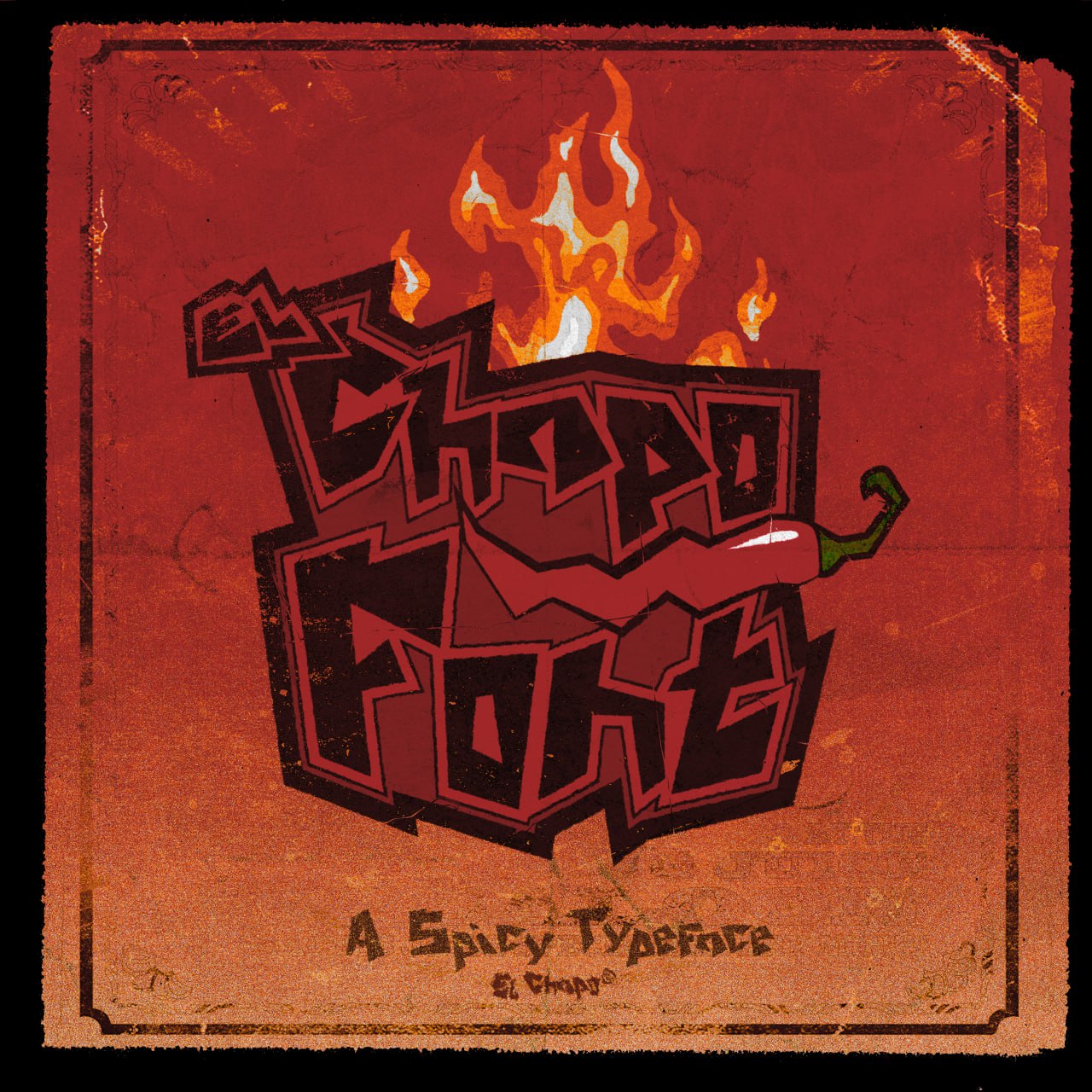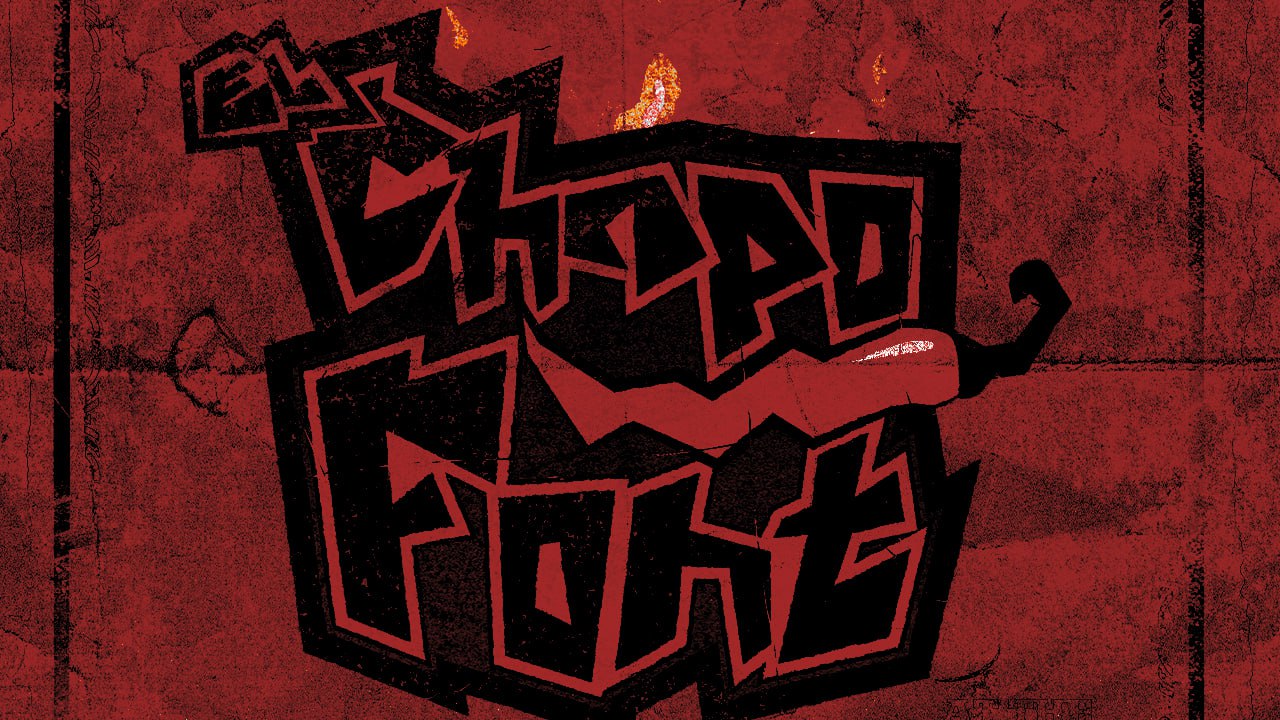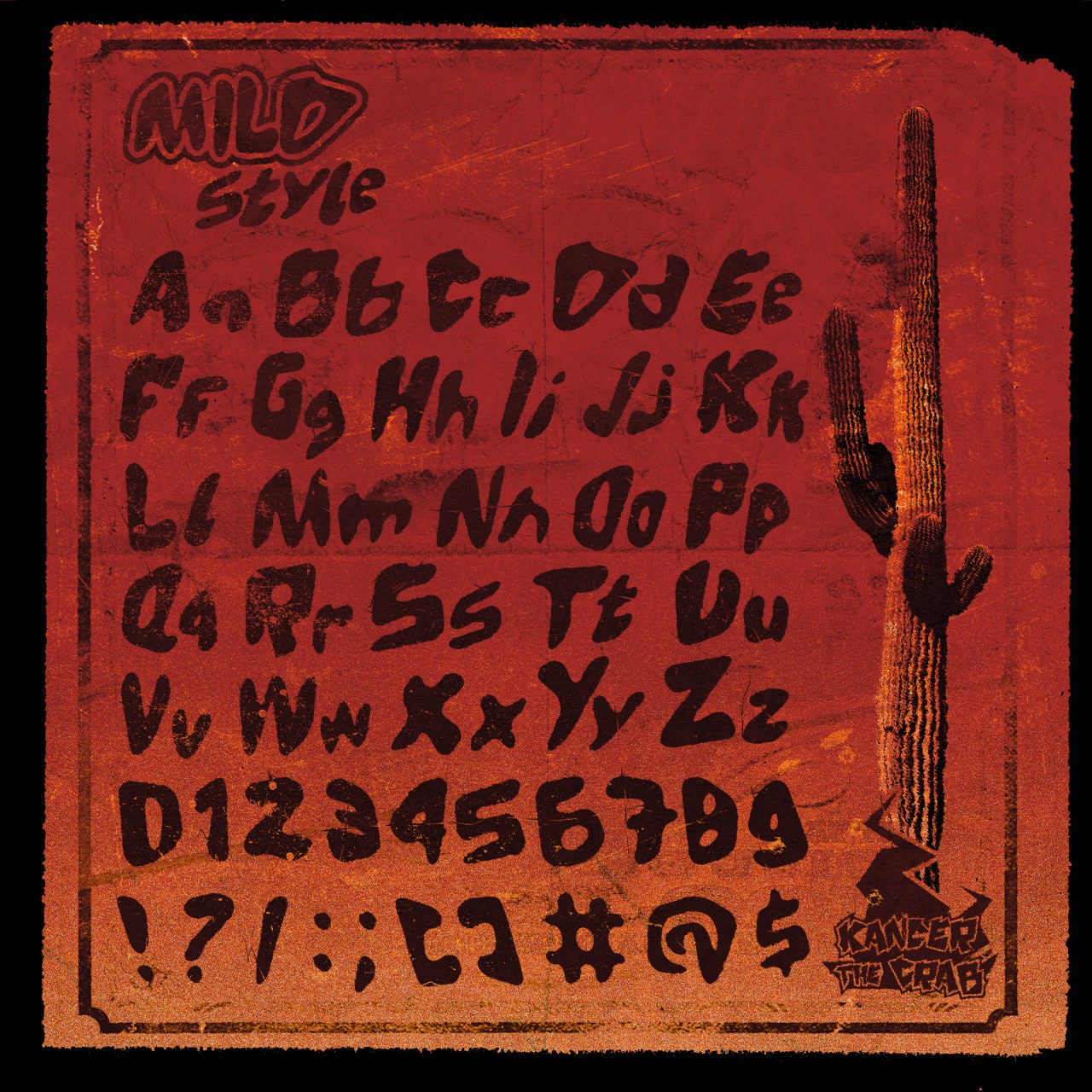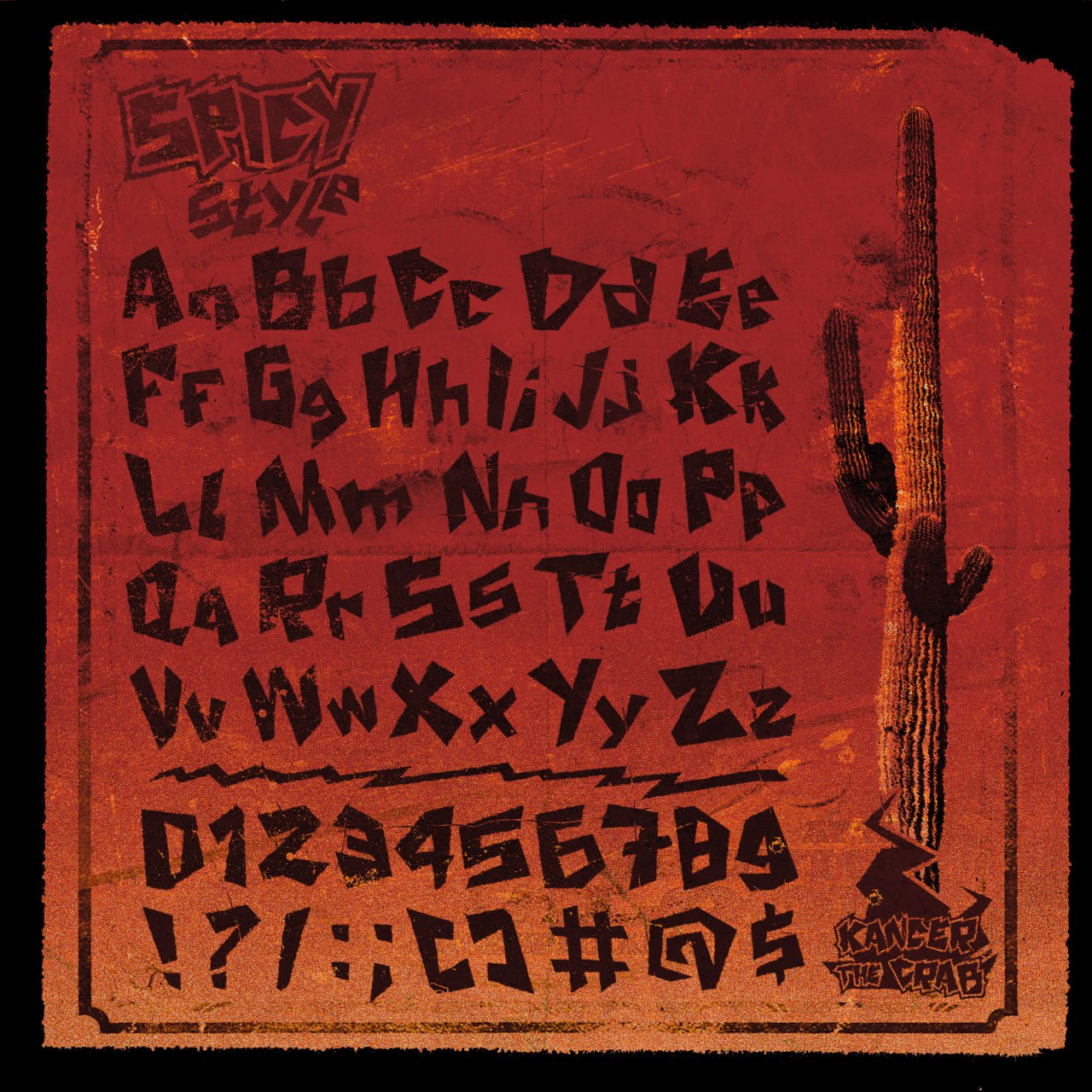
Descubre "El Chapo Font", una tipografía audaz e impactante que aportará un toque vibrante a todos tus proyectos de diseño. Inspirada en la vibrante energía y el calor del desierto, esta fuente es perfecta para quienes buscan una imagen impactante.
Características principales:
Dos estilos únicos: "El Chapo Font" está disponible en dos versiones distintas para satisfacer todos tus deseos creativos:
Estilo suave: Un estilo más suave pero expresivo, ideal para una mayor legibilidad y con una personalidad definida. Perfecto para titulares, logotipos y elementos gráficos que requieren un equilibrio entre audacia y claridad.
Estilo Picante: Para un enfoque más vibrante y dinámico. Este estilo se distingue por sus formas angulares y su aspecto deconstruido, aportando energía pura y un toque de rebeldía a tus diseños. Ideal para pósteres, portadas de álbumes, branding urbano o cualquier proyecto que requiera el máximo impacto.
Conjunto de caracteres completo: cada estilo incluye una gama completa de caracteres en mayúsculas y minúsculas, números (0-9) y una selección de símbolos esenciales (! ? / : ; [ ] # @ $).
Diseño inspirado: Con sus formas de llama y un chile rojo brillante integrado en el logotipo principal, “El Chapo Font” evoca pasión, intensidad y originalidad.
Versatilidad creativa: ya sea que esté trabajando en gráficos de eventos, empaques de productos, ilustraciones, campañas de marketing o medios digitales, esta fuente está diseñada para captar la atención y dejar una impresión duradera.
Estética texturizada: las imágenes de presentación sugieren tipografía con una textura grunge o envejecida, agregando profundidad y carácter auténtico a sus diseños.
Ideal para:
Logotipos y marca
Títulos y encabezados llamativos
Carteles y volantes de eventos
Portadas de álbumes y merchandising musical
Diseño de camisetas y ropa
Redes sociales y contenido en línea
¡Y mucho más!